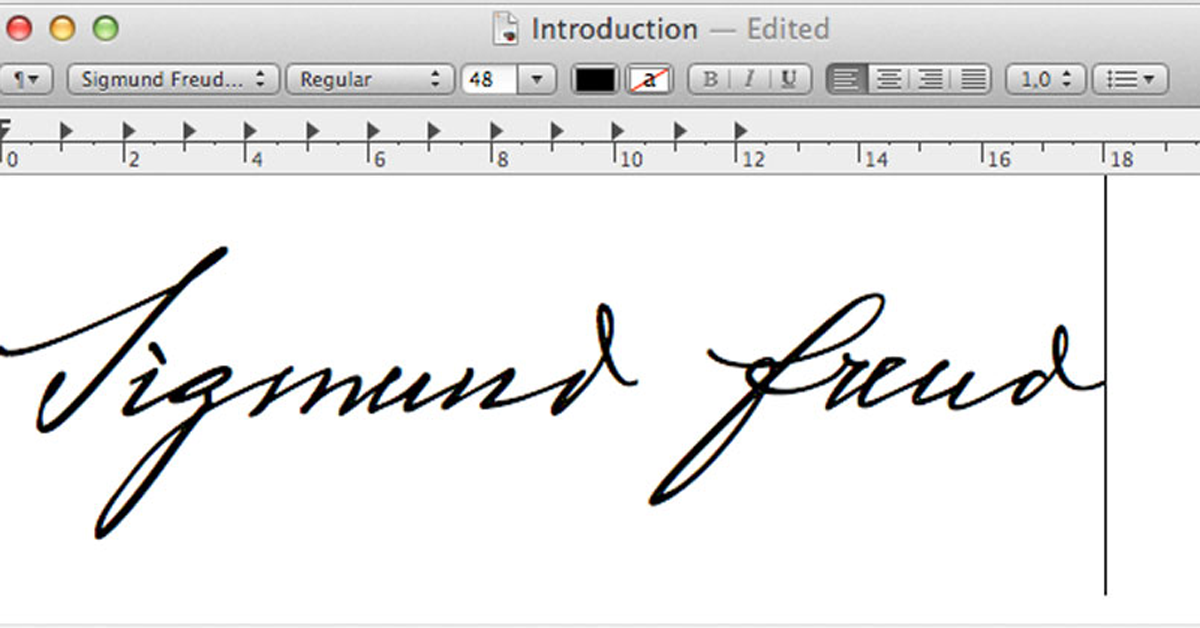
La caligrafía de Einstein, Freud y Martín Lutero hecha tipografía
Un tipógrafo está desarrollando las tipografías basadas en la caligrafía de personalidades históricas como Einstein o Freud.
Fueron muchos litros de tinta los que personalidades históricas como Einstein, Freud o Martín Lutero utilizaron a lo largo de su vida para escribir los incontables documentos que se han convertido en su legado para la humanidad. Movido por la curiosidad de estudiar a fondo la escritura de estos tres hitos humanos de la historia, el tipógrafo alemán Harald Geisler está desarrollando las tipografías basadas en la caligrafía de Freud, Einstein y Lutero.
Para hacerlo, se basa en los escritos y en los documentos que estos hicieron en vida y que se han convertido en patrimonio cultural. Tomando como referencia estos documentos, lo primero que hace Harald Geisler es transcribir los textos, a continuación observa con detenimiento las formas de las letras y la manera en que estas se conectan las unas con las otras, estudiando el movimiento que habría hecho el escritor al dibujarlas. Es entonces cuando empieza a digitalizar los glifos, dibujándolos a mano y tratando de imitar la textura y el trazo de las letras creadas con plumas u otros instrumentos de la época.
Un estudio tan pormenorizado de la escritura de estas personalidades históricas ha permitido a Harald Geisler no solo crear glifos inexistentes en aquella época –como '@', por ejemplo– sino también desarrollar unas tipografías que, como la escritura manual, sufren variaciones. Así, en fuentes como la de Albert Einstein existen entre 5 y 6 glifos diferentes para cada letra, que se van ajustando automáticamente a medida que vamos escribiendo.
De momento, Harald Geisler ha desarrollado las tipografías basadas en la escritura de Albert Einstein, Sigmund Freud y está trabajando en la de Martín Lutero, siempre gracias a campañas de micromecenazgo. Durante este año se ha propuesto desarrollar también la tipografía de Martin Luther King.